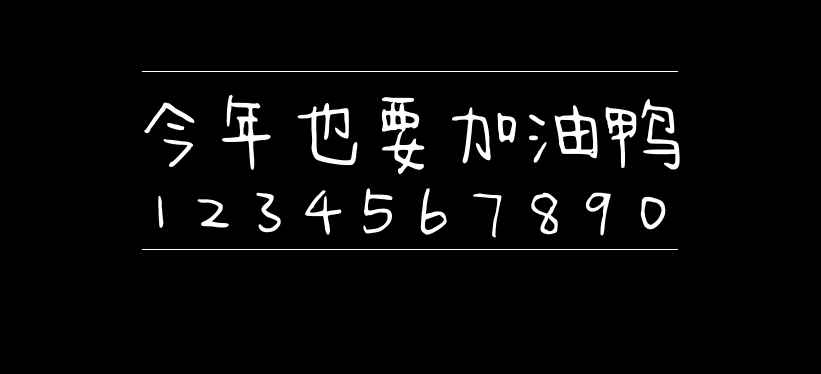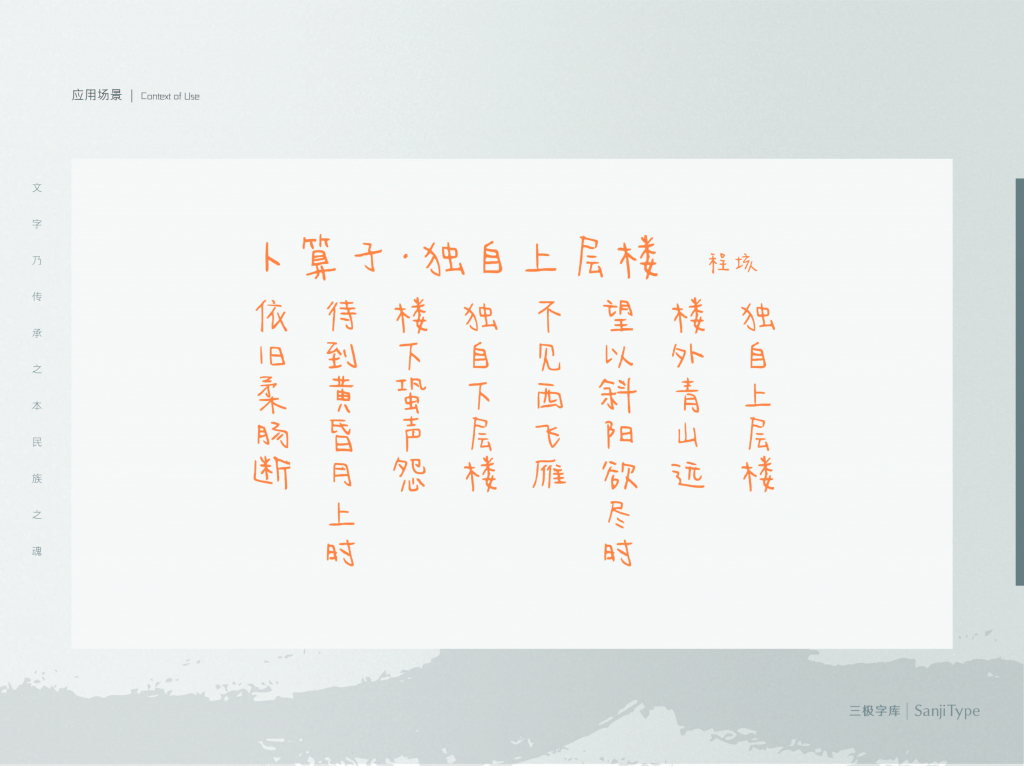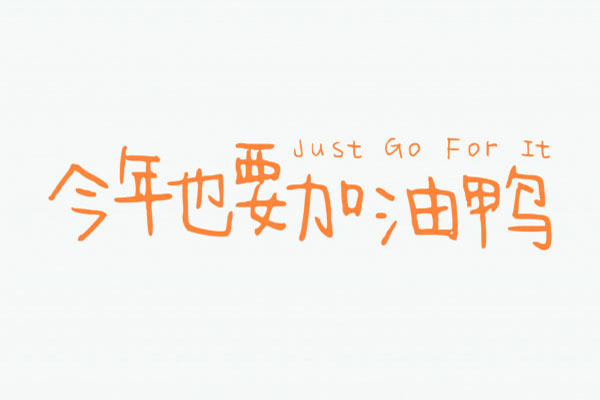
今年也要加油鸭
是的,你没有看错,这款字体的名字就叫:今年也要加油鸭,它是由三极字库的罗碧霞创作的一款手写风格字体。
今年也要加油鸭是一款可商用的硬笔手写字体,具有温柔、婉约、手写风、简约 的风格,可以满足您设计上的各种需求,该字体主要用于海报企宣、书籍、店铺、活动、健康养生 等场景。
今年也要加油鸭字体效果预览